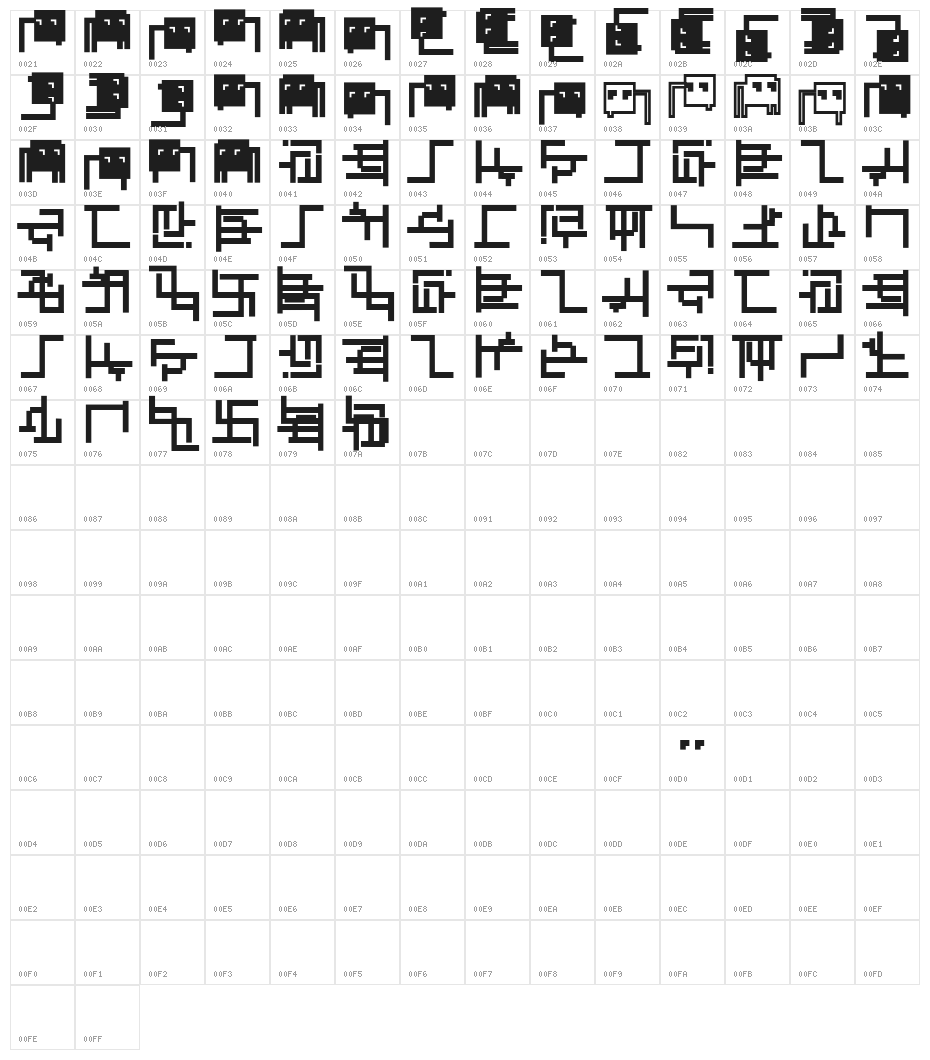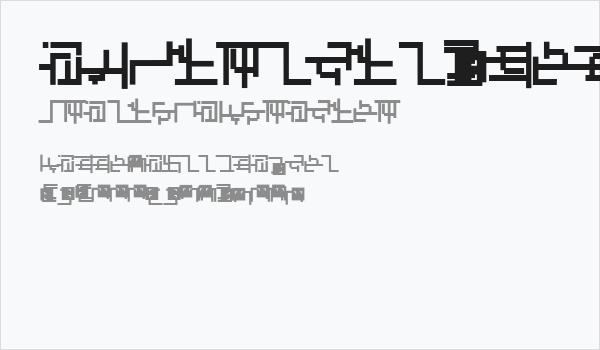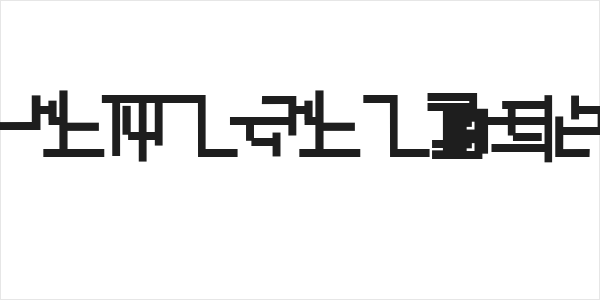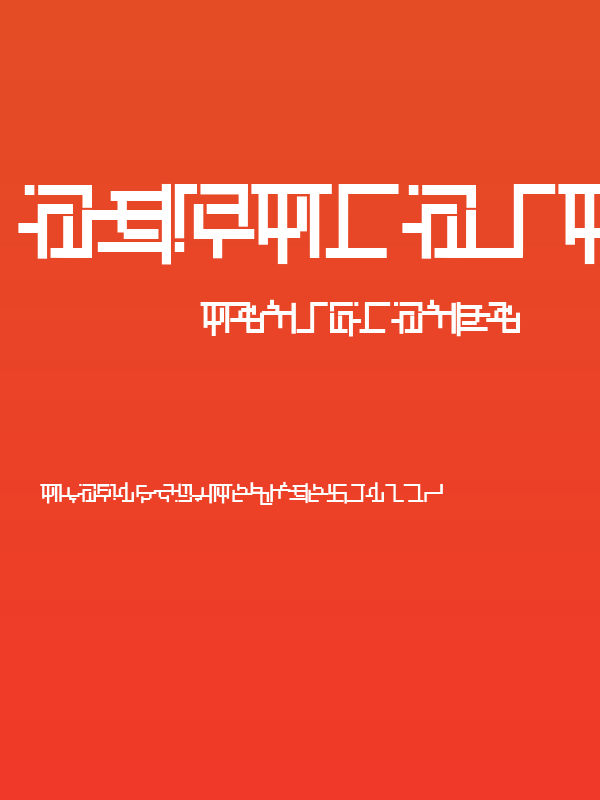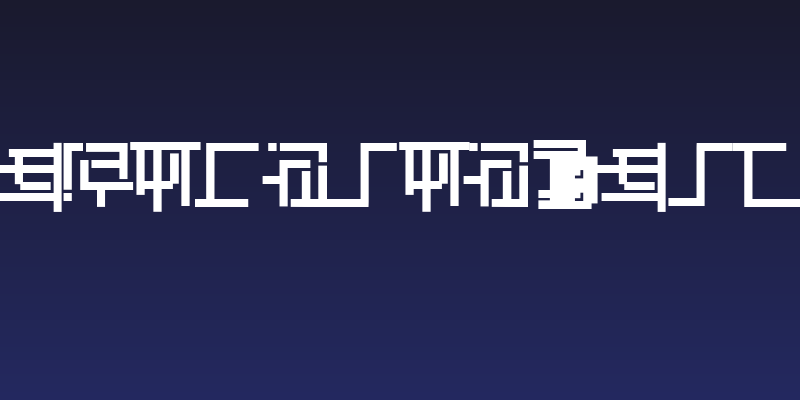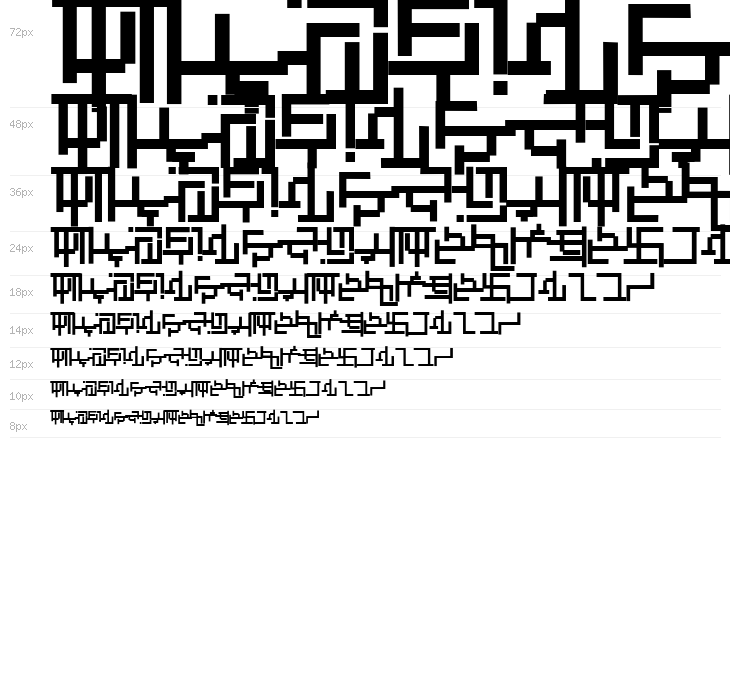
Abstracta-Bold Font
| Categorie | Pixel |
| Caso d'uso | Logos, Headlines, Artistic displays |
| Progetti proposti | Ideal for digital art, experimental design projects, futuristic branding, and tech-themed posters. |